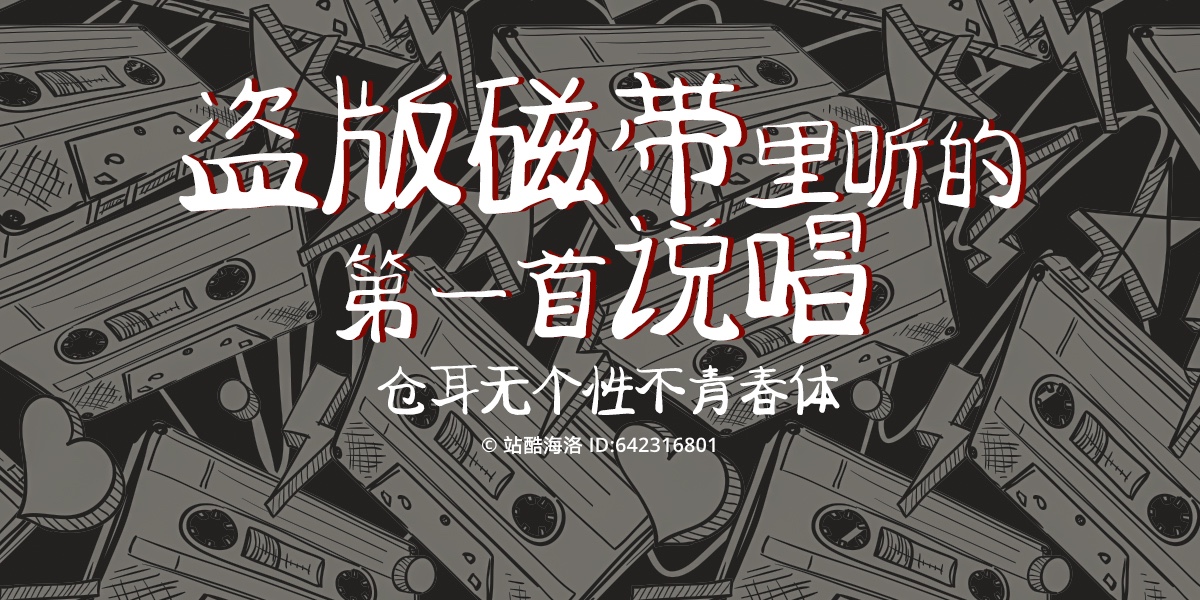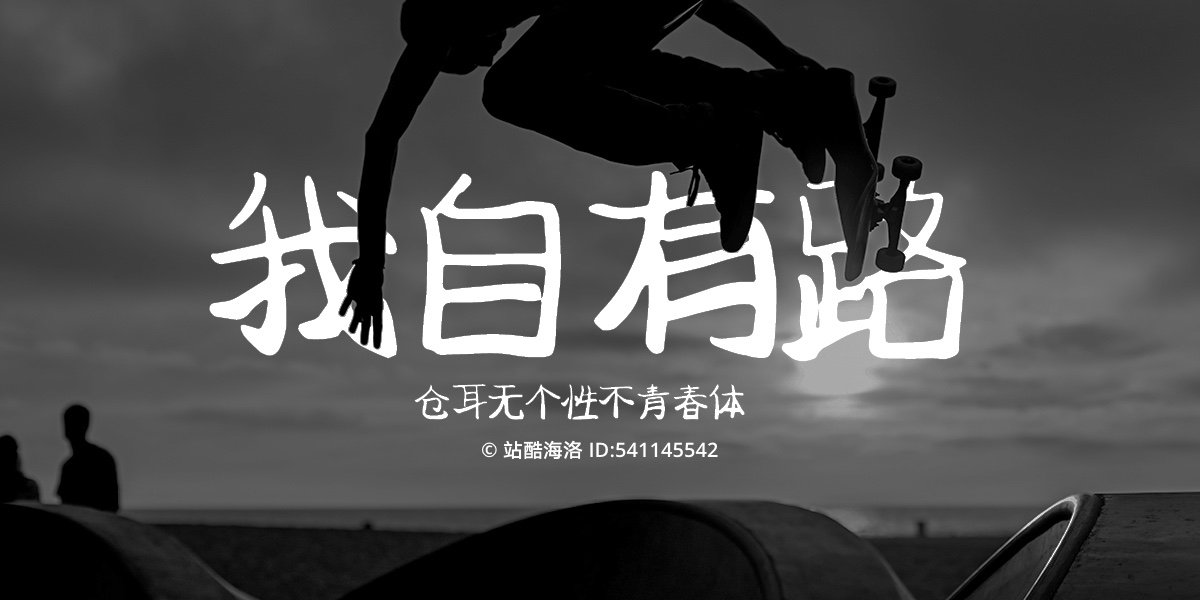
仓耳无个性不青春体
仓耳无个性不青春体,这款手写字体采用软笔书写,笔画从上到下逐渐加粗,字形可爱中不失稳重,是一款创新的手写字体。 为了丰富字体市场的种类资源,增加字体的趣味性,设计师选用粗细变化更加丰富的软笔创作这款字体,将笔画粗细进行调整,每一个字从上到下笔画由粗变细,给字体带来一种全新的视觉冲击。
仓耳无个性不青春体字体介绍